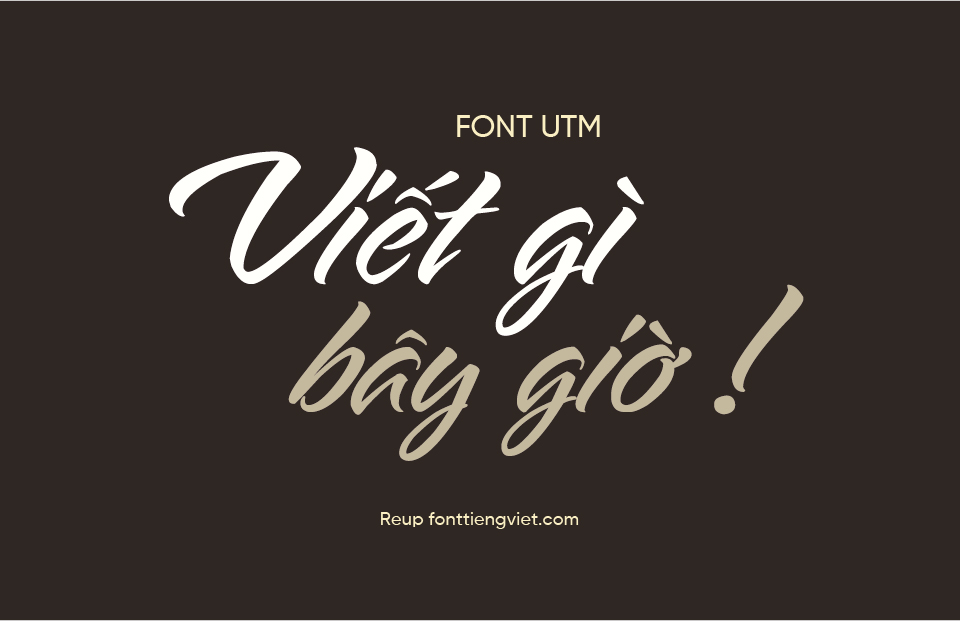
Font việt hóa UTM Alpine KT
Giới thiệu về Font việt hóa UTM Alpine KT
Trong thế giới đồ họa hiện đại, việc lựa chọn Font Miễn Phí chất lượng đóng vai trò then chốt giúp sản phẩm trở nên thu hút và chuyên nghiệp hơn. Font việt hóa UTM Alpine KT là một bộ phông chữ thuộc phong cách Script với những đường nét uyển chuyển, mềm mại nhưng vẫn giữ được sự rõ ràng, dễ đọc. Đây là lựa chọn lý tưởng cho các nhà thiết kế đang tìm kiếm sự phá cách và tinh tế cho các dự án của mình tại Việt Nam.
Đặc điểm nổi bật của bộ Font việt hóa UTM Alpine KT
Phong cách thiết kế độc đáo
Đặc trưng của Font việt hóa UTM Alpine KT nằm ở cấu trúc chữ thanh mảnh kết hợp với các nét nối liền mạch tự nhiên. Bộ font này mang đến cảm giác thủ công, gần gũi nhưng không kém phần sang trọng. Nhờ quá trình việt hóa kỹ lưỡng, các dấu câu tiếng Việt được căn chỉnh chuẩn xác, giúp người dùng không còn lo lắng về lỗi hiển thị khi soạn thảo văn bản hay thiết kế ấn phẩm đồ họa.
Ứng dụng đa dạng trong thực tế
Với vẻ đẹp nghệ thuật sẵn có, Font việt hóa UTM Alpine KT được ứng dụng rộng rãi trong việc thiết kế thiệp mời, bìa sách, menu nhà hàng hoặc các banner quảng cáo thời trang. Trong môi trường học đường, giáo viên và học sinh cũng có thể sử dụng bộ font này để trang trí slide thuyết trình thêm phần sinh động và bắt mắt, tạo ấn tượng tốt cho người xem ngay từ cái nhìn đầu tiên.
Kết luận và tải Font việt hóa UTM Alpine KT